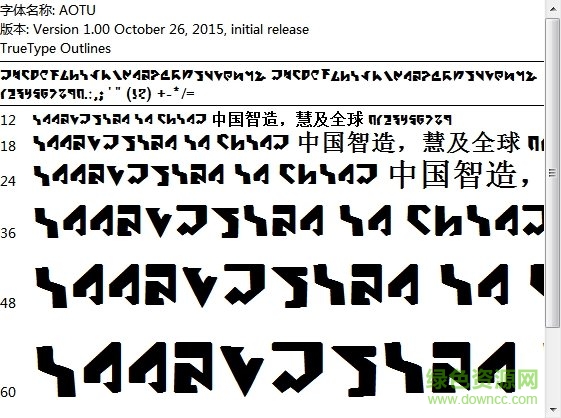
凹凸字體是以凹凸世界文字為模板創(chuàng)作的凹凸文字字體庫【民間版】,讓廣大凹凸迷們可以感受最逼真的視覺效果,給你的手機字體閱讀帶來更親切體驗,綠色資源網(wǎng)獨家推薦!
畫凹凸同人的小伙伴們,還在為模仿官方而努力去翻凹凸文字對照表而心累嘛?
不用擔心!這里已經(jīng)把超級方便的凹凸文字字體庫【民間版】做出來啦!
因為是民間版,制作的并沒有官方的精細,字體之間會出現(xiàn)輕微的高低錯落的感覺,請見諒!